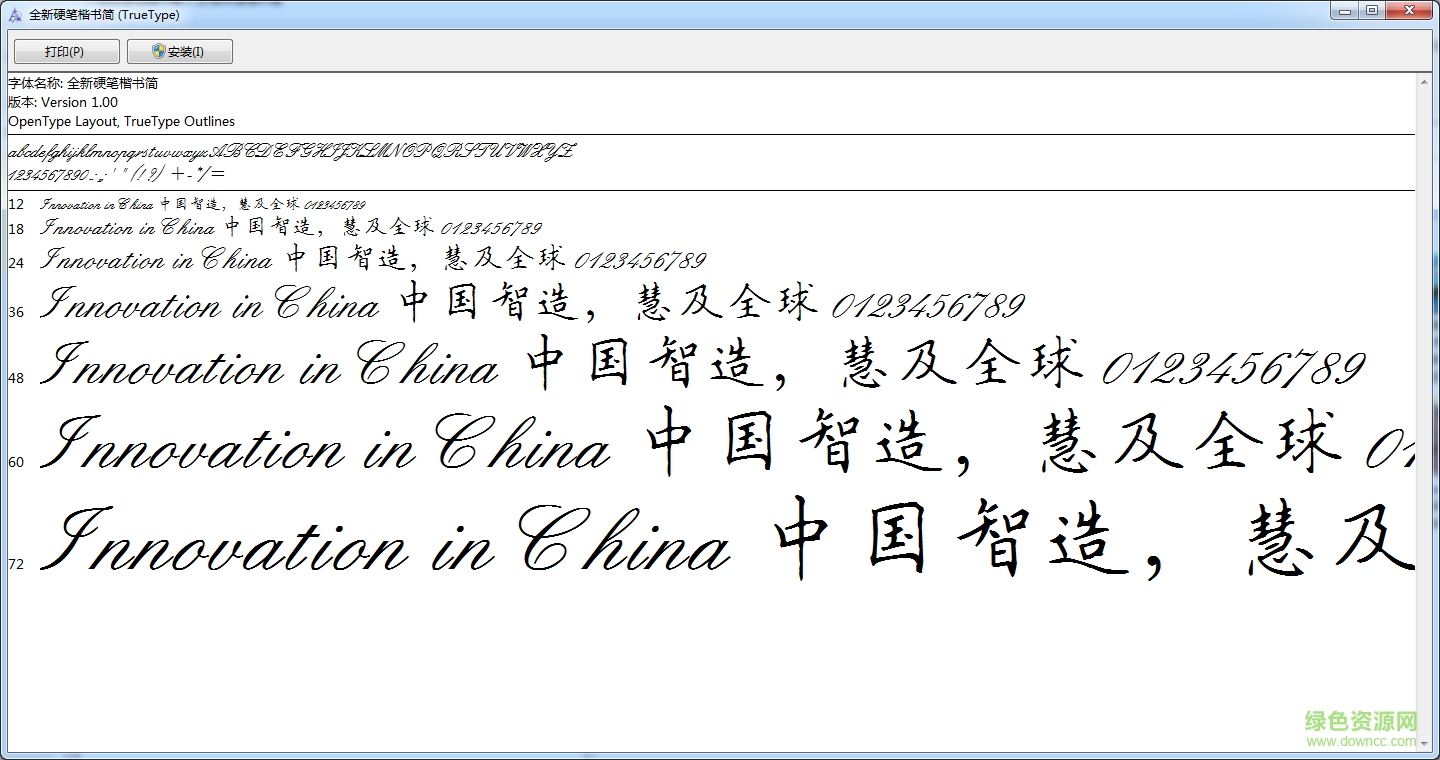
qxyingbikai
qxyingbikai全新硬筆楷書(shū)簡(jiǎn)字體是一款將藝術(shù)性和實(shí)用性完美結(jié)合的高品質(zhì)楷書(shū)字體,字體的布局構(gòu)形都非常講究,筆畫(huà)整齊,統(tǒng)一協(xié)調(diào),歡迎大家在綠色資源網(wǎng)下載!
楷書(shū)字體學(xué)習(xí)方法
【結(jié)構(gòu)方整】
鋼筆楷書(shū)在結(jié)構(gòu)上強(qiáng)調(diào)筆畫(huà)和部首均衡分布、重心平穩(wěn)、比例適當(dāng)、字形端正、合乎規(guī)范。字與字排列在一起時(shí)要大小勻稱(chēng)、行款整齊。雖然也有形態(tài)上的參差變化,但從總體上看仍是整齊工整的。
【講究用筆】
鋼筆楷書(shū)的筆畫(huà)有提頓、藏露、方圓、快慢等用筆方法。不同的用筆方法產(chǎn)生不同的形態(tài)、質(zhì)感的線條,不同的線條需要不同的用筆方法去體現(xiàn)。